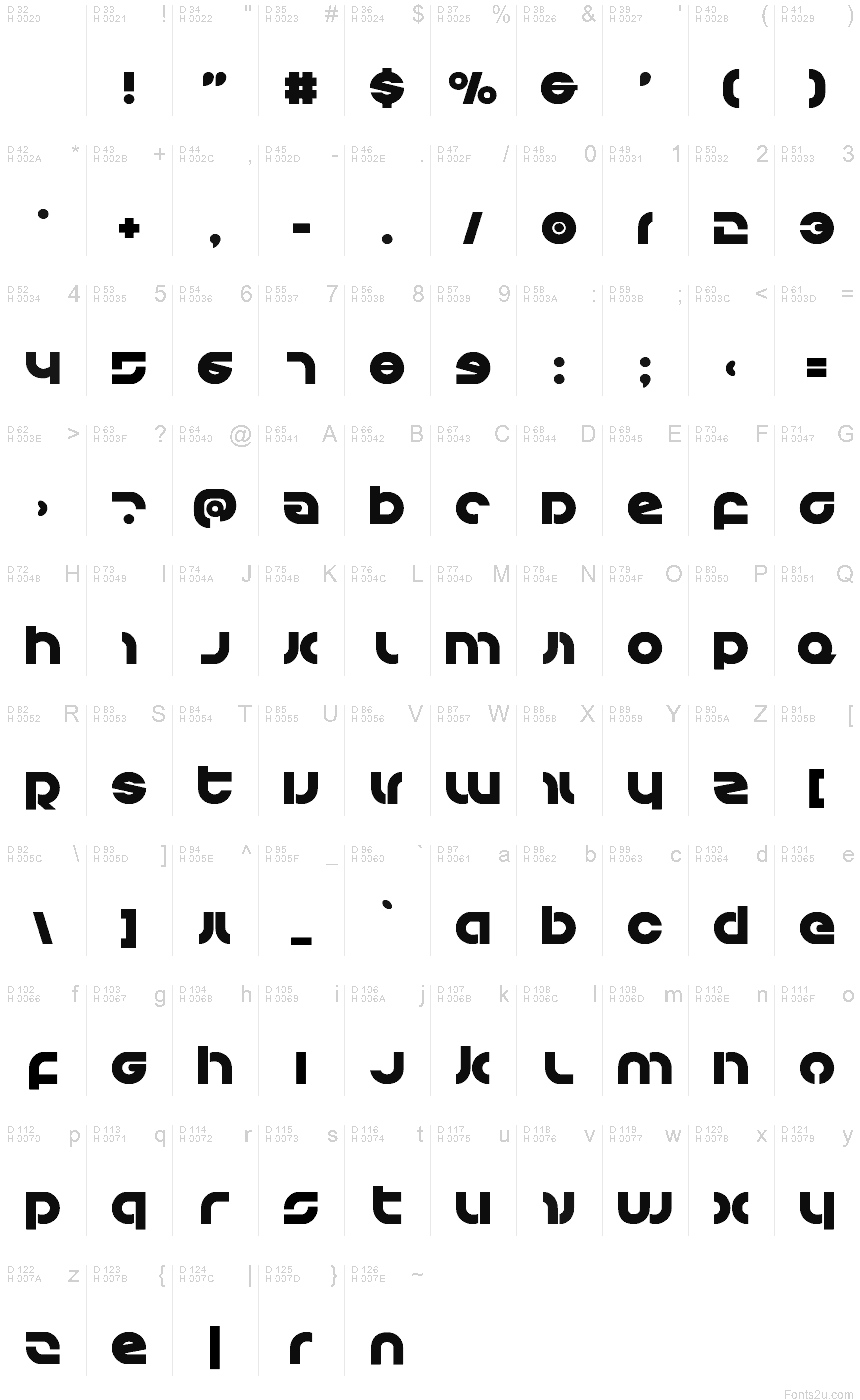
Kovacs
Kovacs od Iconian Fonts to darmowy, techno-futurystyczny krój typu display. Jego masywne, ultra-obłe kształty łączą się niczym lśniące części maszyn, a koliste oczka liter przecięte są ostrymi, pionowymi cięciami, przypominającymi otwory na klucze lub porty dokujące. Rytm jest gęsty i mechaniczny, więc każde słowo wygląda jak indywidualne logo, zwłaszcza gdy tekst jest duży i ma wokół siebie trochę wolnej przestrzeni.
Kovacs pozwala nadać wyrazisty, sci-fi klimat tytułom gier, identyfikacji e-sportowej, plakatom filmowym, ulotkom imprezowym, podcastom technologicznym czy okładkom muzyki elektronicznej. Ten darmowy font najlepiej sprawdza się w nagłówkach, wspierany przez czysty, geometryczny krój bezszeryfowy w tekście głównym. Wypróbuj szerokie światło między literami i duże marginesy, aby wyeksponować jego rzeźbiarskie krzywizny i futurystyczną sylwetkę.